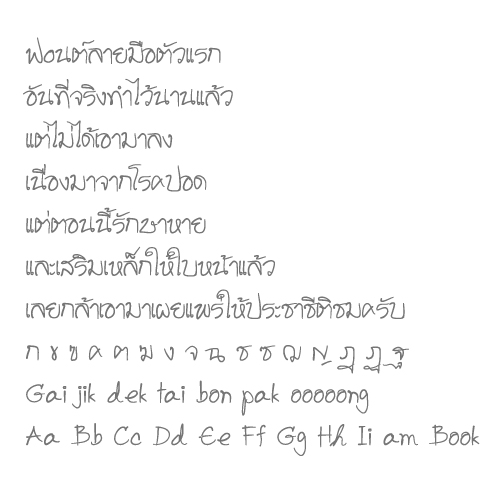
ลองเอาฟ๐นต์ตัวแรกมาให้ดูครับ
เป็นฟ๐นต์ลายมือตัวเองที่ตั้งใจทำ(มากๆ) ตัวอักษรทุกตัวเลยมีเอกลักษณ์ของตัวเอง และไม่เข้ากัน  :08:
แต่เมื่อมันเป็นฟ๐นต์แรก เลยไม่อยากแก้
น้อมรับคำติชมครับ
ส่วนติชม ...  :42:
ขอบคำนี้อะ "ตัวอักษรทุกตัวเลยมีเอกลักษณ์ของตัวเอง และไม่เข้ากัน"   :43:
ฟอนท์ลายมือมันก็เป็นเอกลักษณ์ของมันอยู่แล้วครับ
ดูตัวสระ ใ มันจะไปทับตัววรรณยุกต์ข้างหน้า อาจจะทำให้อ่านยากครับ
สารภาพบาป : ช. ผมเห็นเป็น ธ. แหละ
น้อมรับ  :42:
จะแก้เท่าที่แก้ได้ครับ
ให้ระวังพวกตัวม้วน (ใไโ)ตัวพาล(ศส)ไม่ให้ไปตีกับตัวลอย ( ็  ้  ่  ๊)ไว้นะครับ มันมักจะไปตีกัน
ต ค ช
เท่ห์มากครับ สมเป็นลายมือ
ไม่มีติครับ ผมไม่ค่อยรู้เรื่องฟอนต์เท่าไร ไม่อยากพูดอะไร
ยิ่งไม่รู้เรื่องฟ๐นต์เท่าไหร่ยิ่งต้องพูดครับ
สำหรับผมแล้ว
เสียงจากผู้ใช้คือเสียงสวรรค์มากกว่าฟังแต่คนทำมาคุยกันเอง
เรื่องที่จะติก้มีนิดเดียวครับ
คือช่องไฟอีตรงตัว เ แ หรือตัวแคบๆ มันแคบไป
ลองขยายให้หายใจสะดวกอีกหน่อย
ให้มันตีกันให้ตายห่านตายหงส์ไปให้หมดก็สนุกดีนะ
คือช่องไฟอีตรงตัว เ แ หรือตัวแคบๆ มันแคบไป
ลองขยายให้หายใจสะดวกอีกหน่อย
ให้มันตีกันให้ตายห่านตายหงส์ไปให้หมดก็สนุกดีนะ